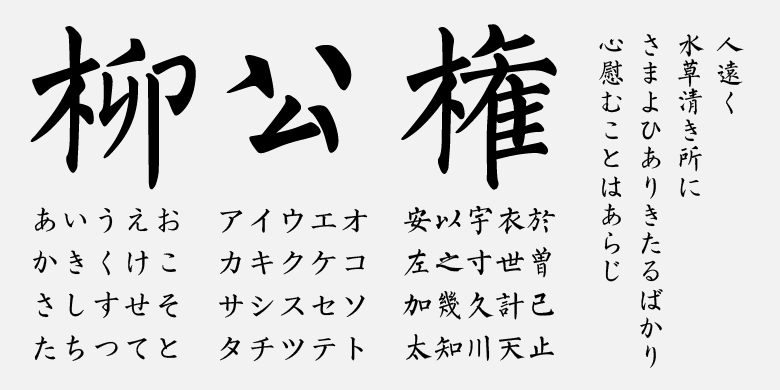
FZ Liu Gongquan Kai JP
字体品牌: 方正字库 中华精品字库 整理/设计:苏新诗 字体分类:常规书写·毛笔 字体属性:外文 字符集:Unicode 发布时间: 2024
柳公权(778-865年)、唐代の書道家。字は誠懸。京兆华原(現在の山西省運城市解州鎮)出身。官は太子少師に至る。書に優れ、特に楷書で知られる。王羲之から学び始め、近代の書法を広く研究し、顔真卿や欧陽詢の影響を受け、力強く緻密な構造を持ち、独自のスタイルを確立した。後世に大きな影響を与え、「顔柳」と顔真卿と並んで称えられる。多くの碑文があり、『玄秘塔碑』、『金剛経』、『神策軍碑』が最も有名。書跡には『送梨帖题跋』がある。字体の特徴としては、『玄秘塔碑』と『神策軍碑』を主な開発基としており、筆勢は力強く、形は整然としており、厳密さの中にも疎らな美が表れる。
字体ブランド:方正字庫、中華精品字庫
監修:胡迪軍
整理/デザイン:蘇新詩
字体分類:筆書体・毛筆
字体属性:精品字